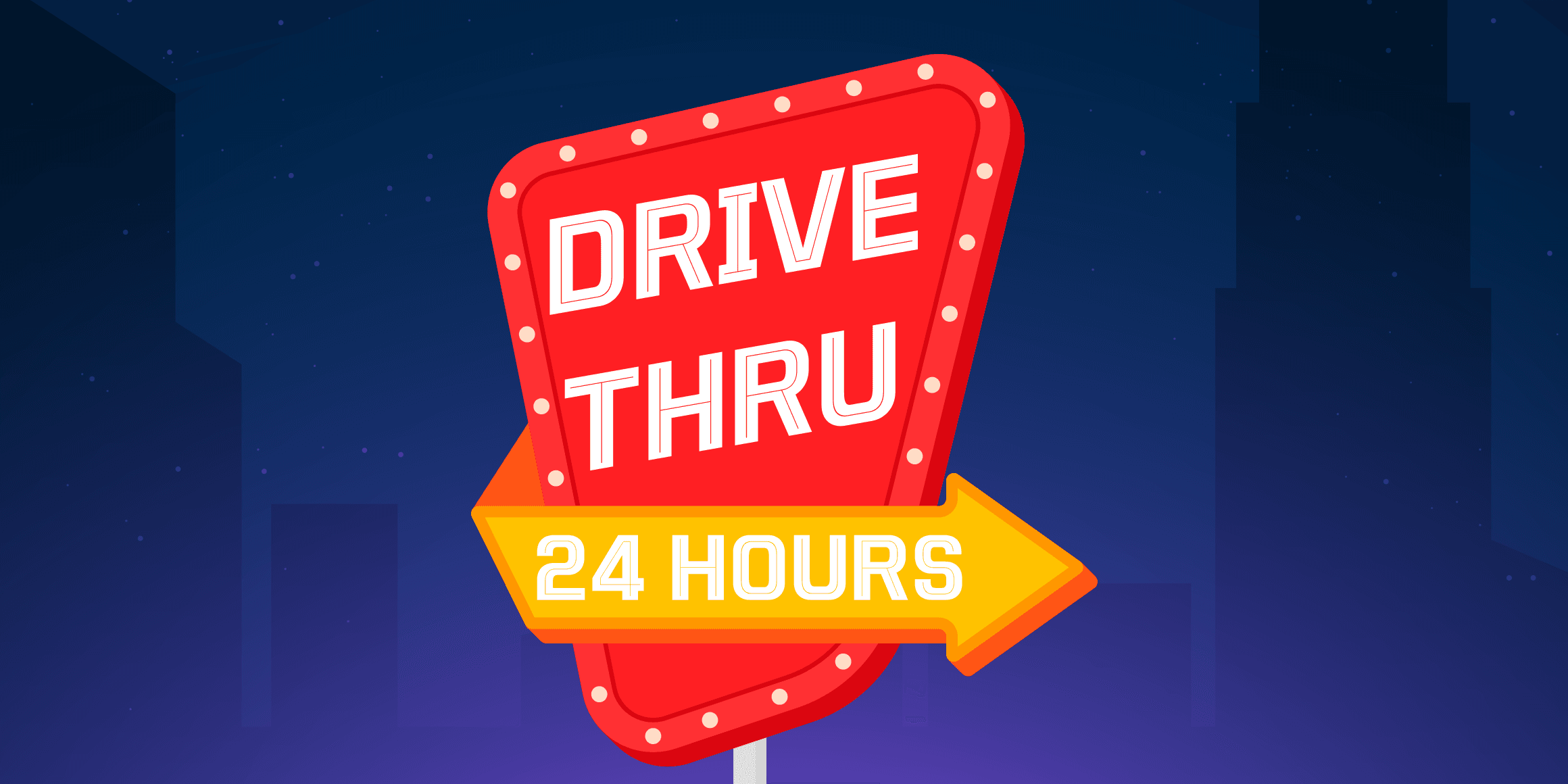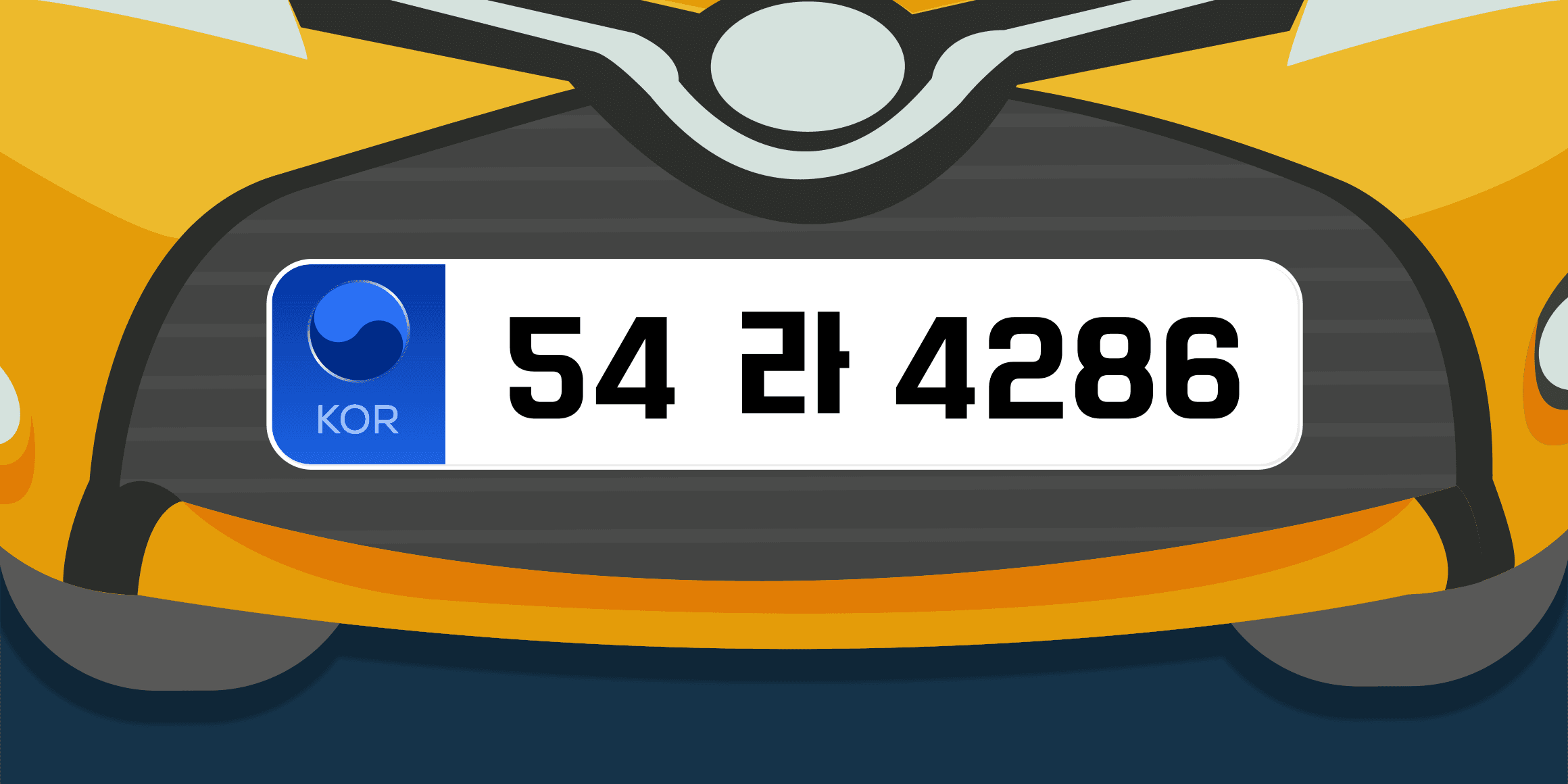
하이웨이
텐실형 디스플레이 서체
[ 폰트 제작사 ]
Design210
도로 표지판에서 영감을 받은 스텐실형 디스플레이 서체로, 산업적이면서도 현대적인 감각을 지닙니다. 획이 곳곳에 끊김을 갖춰 시각적 리듬감을 주며, 제목·로고·패키지 등에서 강한 인상을 남길 수 있습니다. 특히 테크놀로지, 모빌리티 관련 브랜드나 스트리트 패션, 힙스터 감성의 디자인에 적합합니다.